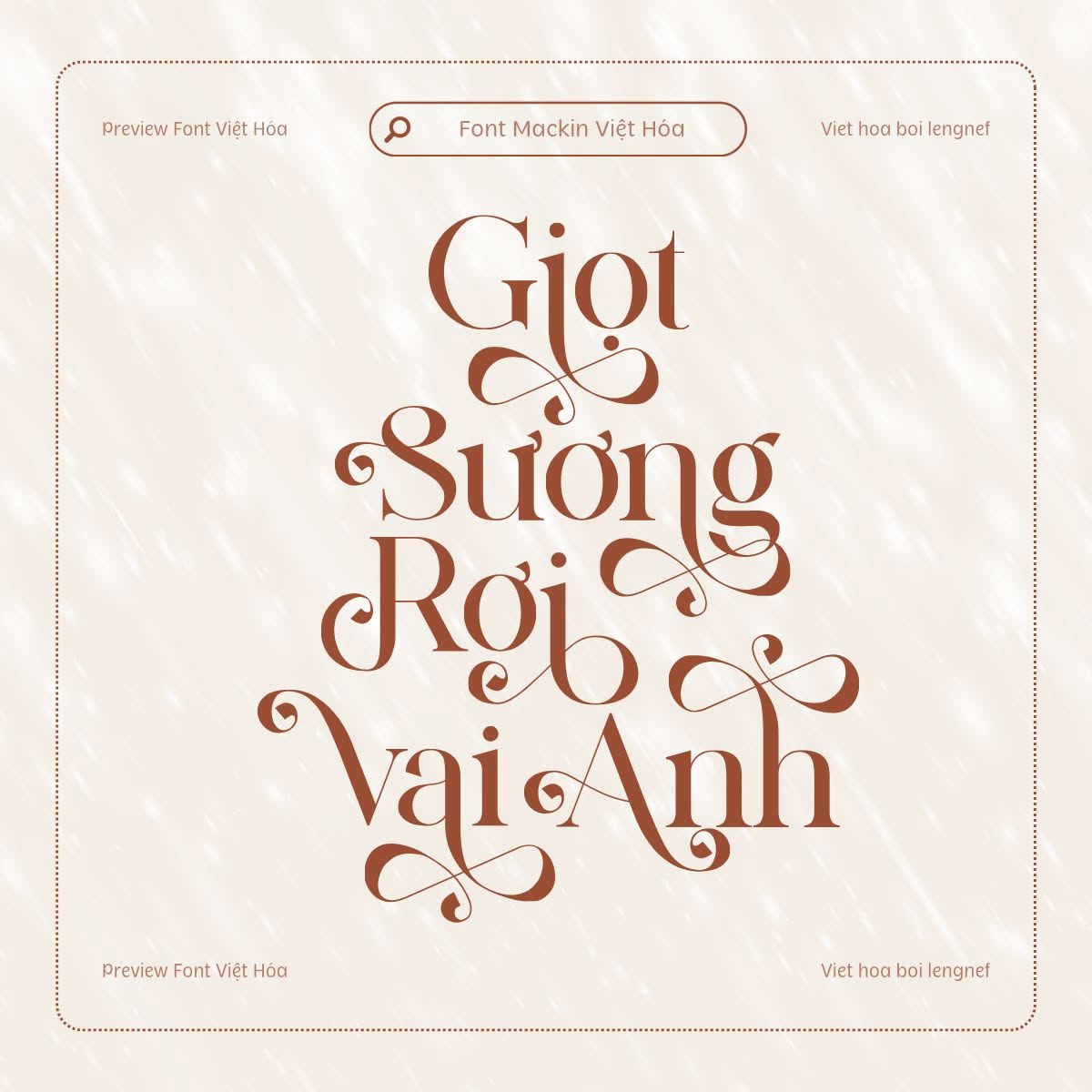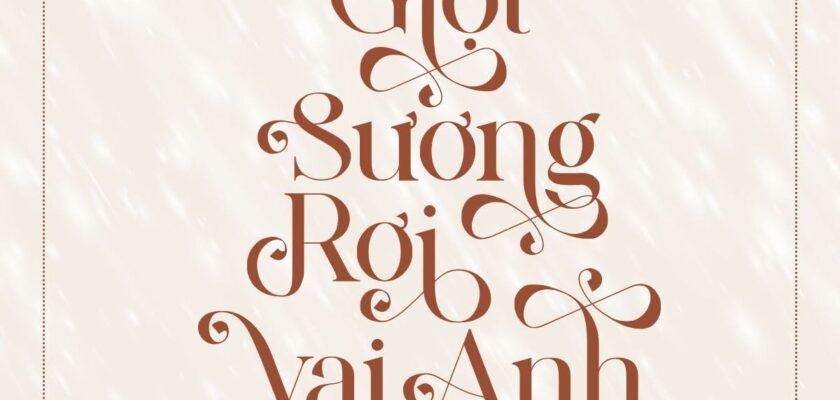
Việt hóa theo yêu cầu 18 || LF Mackin
- Tác giả: Aqeel_Art
- Việt hóa: lengnef
Mackin thuộc font serif được lấy cảm hứng từ logo tối giản nổi tiếng. Gồm nhiều glyph uốn lượn hoàn hảo cho mục đích thiết kế logo, thương hiệu, tờ rơi, video, quảng cáo,…